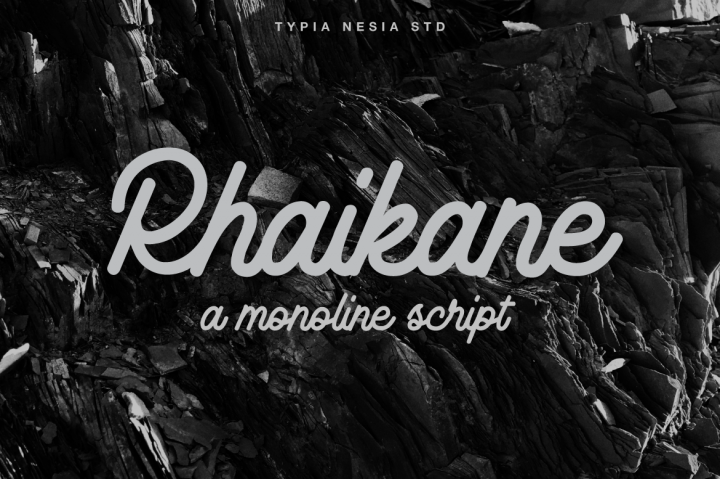
Bem-vindo! Estamos muito felizes em apresentar Rhaikane – uma elegante tipografia de script vintage monolínea. Desenvolvida pelo designer Hamilton, Rhaikane Script é perfeito para aplicação em vários estilos de criação visual. Perfeito para criar um logo para sua marca ou seu negócio pessoal, personalizar camisetas, projetar uma poster com citações, embalar seus produtos de forma criativa, fazer capas de livros cheios de estilo e design de cartazes, ou qualquer outro projeto que precise de uma caligrafia monolínea. Este é um grande aliado para quem busca tornar suas criações ainda mais únicas e memoráveis. Se você está procurando por uma fonte de script vintage monolínea para seus projetos digitais, Rhaikane é definitivamente uma opção a ser considerada.